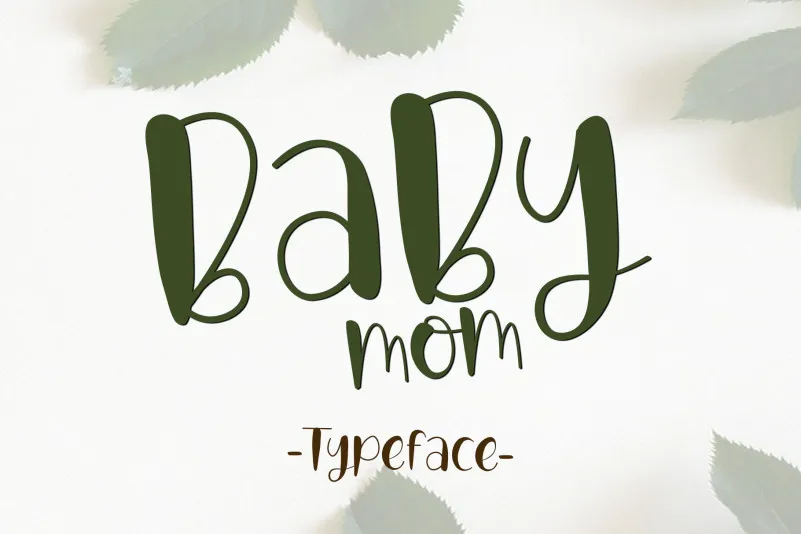
Babymom Font – Fonte Grátis
Babymom Font
A fonte ‘Babymom Font’ é uma elegante escolha para aqueles que buscam uma fonte script ligeiramente descontraída e sofisticada. Ela traz um charme relaxado e leve, ideal para aplicação em materiais pessoais ou gráficos infantis. Seja você criando cartões de visita, letras para seu blog, revistas infantis ou até mesmo materiais publicitários, a ‘Babymom Font’ se tornará uma ferramenta essencial na sua biblioteca de fontes digitais. A característica peculiar dessa fonte é sua capacidade de enriquecer e dar um toque especial a qualquer obra que escolha usá-la, seja ela uma página editorial ou até mesmo um simples cartão de aparição. Não há dúvida de que o ‘Babymom Font’ se destaca como uma font script perfeita para designers gráficos.